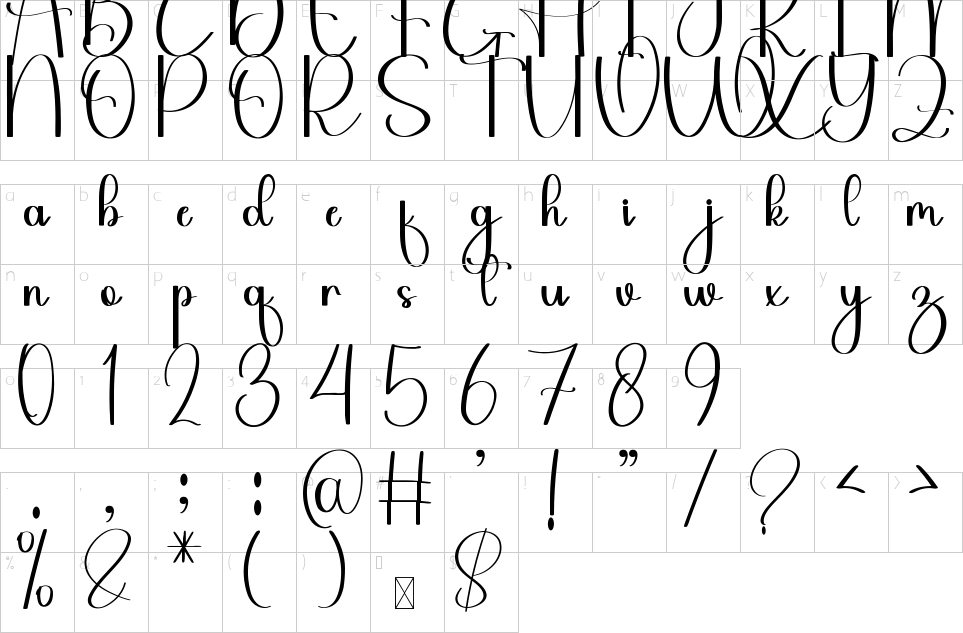
Antumn Font – Download Grátis
Descubra a elegância da Antumn font, uma opção gratuita que combina facilidade de uso com um design moderno e sofisticado. Com sua elegante tipografia, a Antumn font é ideal para qualquer projeto gráfico que busca um visual atraente e profissional. Desenvolvida pela InermediaSTUDIO, essa fonte pode ser usada tanto em sistemas operacionais Windows quanto Mac, oferecendo flexibilidade para qualquer ambiente de trabalho. Com uma fácil instalação e muitas opções de personalização, a Antumn font é uma escolha ideal para designers e criativos em busca de uma fonte perfeita para seus projetos. Há algo fascinante nela, algo que desperta o interesse dos criativos e dos amantes da boa e velha tipografia. Descubra agora a Antumn font e experimente sua versatilidade.